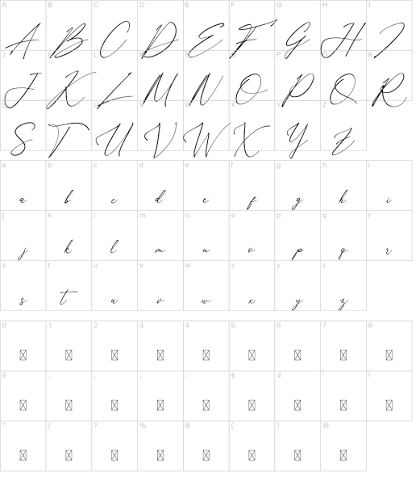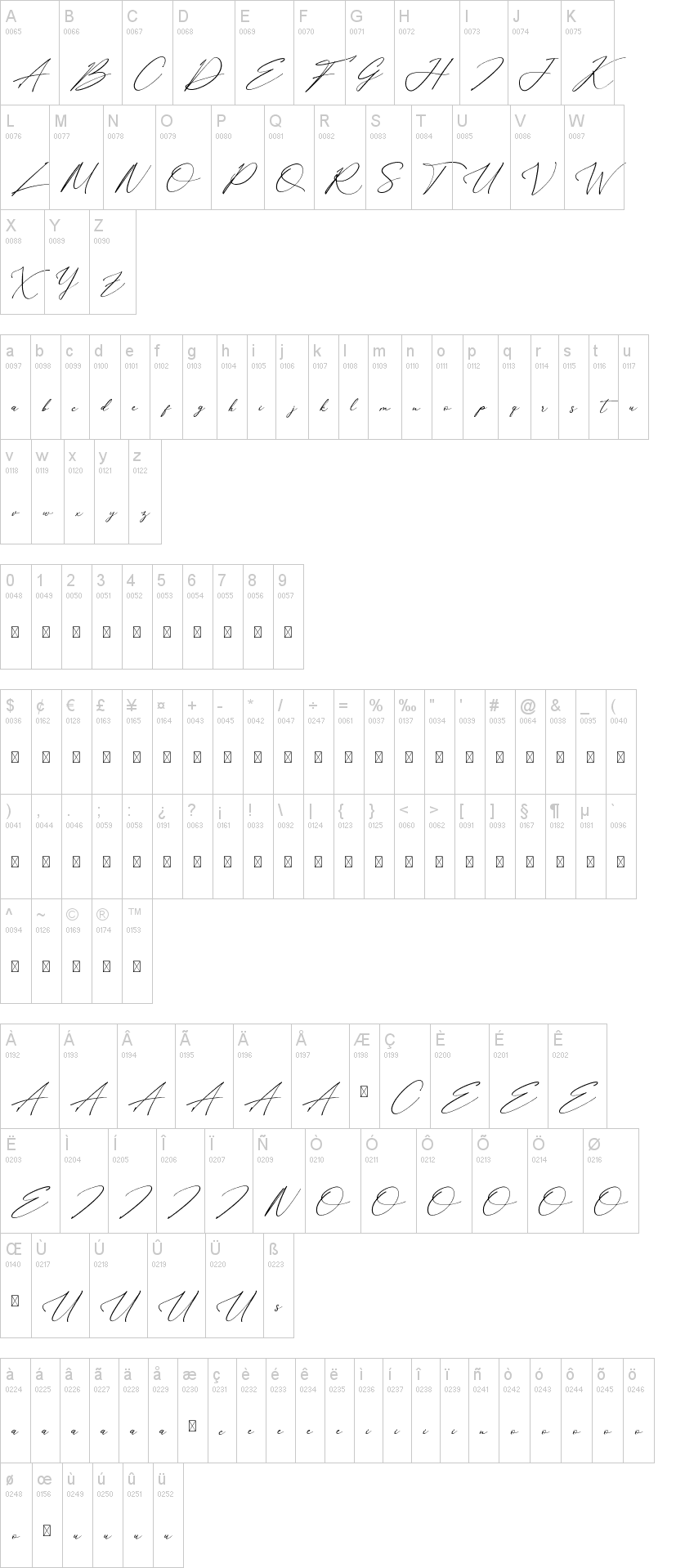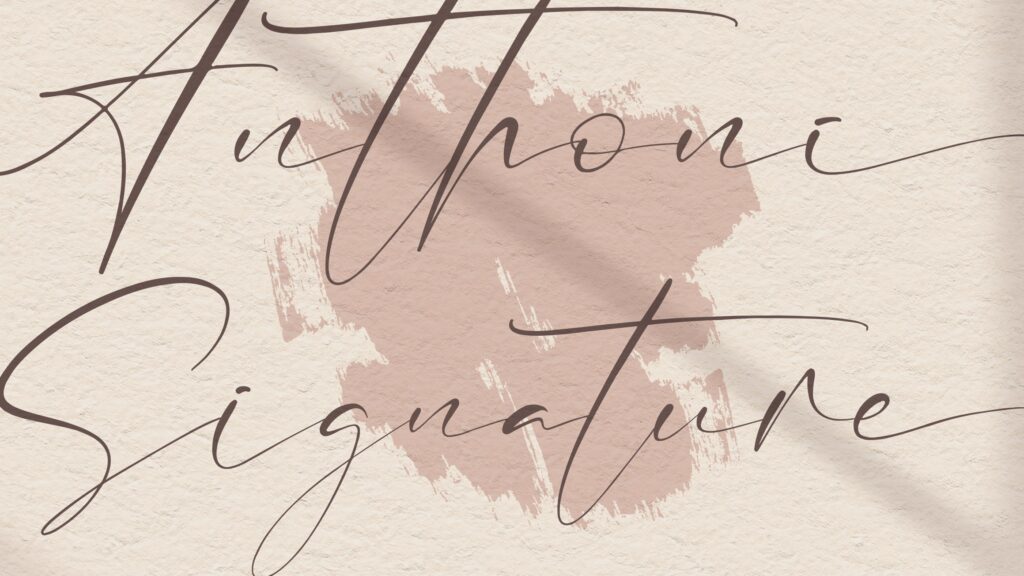
Anthoni Signature font là bộ phông chữ thuộc dòng Signature Script mô phỏng chân thực nét chữ ký tay bằng bút dạ kim cao cấp với các đường nét thanh mảnh, liền mạch và tràn đầy sự tự tin. Mang vẻ ngoài phóng khoáng, hiện đại và đậm dấu ấn cá nhân, kiểu chữ này giúp các kiến trúc sư, nhà thiết kế mang lại sự tinh tế cho các bản vẽ phối cảnh biệt thự sinh thái, sảnh đón tiếp resort sang trọng hay bộ nhận diện thương hiệu kiến trúc đẳng cấp.
Nét bút thanh mảnh và phong thái đĩnh đạc của Anthoni Signature font
Điểm cuốn hút của Anthoni Signature font nằm ở nhịp điệu đưa bút mượt mà, tạo nên các đường liên kết chữ tự nhiên và những nét móc vươn dài đầy thanh thoát. Cấu trúc chữ sở hữu độ mở ký tự thoáng đãng và độ dày nét mảnh dẻ, giúp văn bản toát lên vẻ trang nhã, xóa tan sự cứng nhắc của các khối chữ in ấn truyền thống.
Sự ổn định về mặt cảm xúc của dòng font này giúp truyền tải thông điệp về sự cam kết, tính chuyên nghiệp và sự tận tâm của người kiến tạo không gian. Khi xuất hiện trên các bề mặt vật liệu kiến trúc hiện đại như vách kính trong suốt, kim loại mạ vàng gương hay gỗ tự nhiên sáng màu trong các căn nhà lắp ghép nghỉ dưỡng, Anthoni Signature tạo nên điểm nhấn nhẹ nhàng, làm dịu đi cảm giác thô cứng của các khối kết cấu chịu lực.
| Phân loại phong cách | Signature Script / Monoline / Elegant Handwritten |
| Mục đích phù hợp | Chữ ký kiến trúc sư, biển tên villa, logo cá nhân |
Tư vấn từ chuyên viên: Anthoni Signature sở hữu các đường nét uốn lượn mảnh mai và bay bổng. Để bản thiết kế đạt hiệu quả thẩm mỹ tốt, bạn chỉ nên sử dụng phông chữ này cho các tiêu đề chính, lời tựa ngắn hoặc chữ ký tác giả. Phần nội dung mô tả kỹ thuật chi tiết nên đi kèm một phông chữ không chân thanh mảnh hơn để người xem tiếp nhận thông tin dễ dàng.
03 Ứng dụng phông chữ Anthoni Signature vào công trình thực tế
Nhờ diện mạo lịch thiệp và tính nghệ thuật phong phú, bộ phông chữ này mang lại giá trị thực tế lớn trong khâu tạo điểm nhấn cho các công trình hiện đại:
- Chữ ký Kiến Trúc Sư trên Bản vẽ Ý tưởng: Đặt Anthoni Signature font ở góc bản vẽ phối cảnh 3D như một dấu ấn xác thực của tác giả giúp hồ sơ thiết kế toát lên vẻ chỉn chu và niềm kiêu hãnh của người kiến tạo.
- Biển tên cho Villa và Khu nghỉ dưỡng Cao cấp: Những nét chữ uốn lượn thanh lịch của Anthoni Signature rất ăn ý khi gia công chữ nổi bằng inox vàng xước trên vách đá tự nhiên, mang lại diện mạo sang trọng và chào đón du khách ghé thăm.
- Biển chào mừng và Số phòng cá nhân hóa: Phông chữ này khi khắc laser chìm trên gỗ óc chó hoặc in trên kính mờ sẽ giúp các căn phòng trong khu nhà lắp ghép toát lên chất nghệ thuật tao nhã, mang lại cảm giác được trân trọng cho khách lưu trú.
03 Lưu ý bố cục font Anthoni Signature luôn nhẹ nhàng và bay bổng
Để khai thác hiệu quả vẻ đẹp của dòng font chữ ký này mà không gây cảm giác rối mắt cho bản vẽ, người thiết kế nên lưu tâm một số kinh nghiệm sau:
- Tránh viết hoa toàn bộ cụm từ: Các ký tự hoa của Anthoni Signature có biên độ uốn lượn rộng và nét nối dài. Việc viết hoa liên tiếp nhiều chữ cái sẽ làm các nét xoắn chồng lấn lên nhau, gây mất trật tự bố cục và làm câu văn trở nên khó đọc.
- Kiểm soát khoảng cách dòng: Do các nét vươn lên trên và hạ xuống dưới của phông chữ khá dài, bạn nên thiết lập khoảng cách dòng thoáng đãng để các ký tự không bị chạm nhau, giữ được sự thông thoáng cho khung thiết kế.
- Bố trí nền màu đơn sắc hoặc mờ nhẹ: Anthoni Signature phát huy hiệu quả thị giác cao khi đặt trên các nền màu đơn sắc nhạt hoặc hình ảnh phối cảnh mờ nhẹ, giúp các đường nét thanh mảnh được tôn vinh rõ ràng mà không bị chìm vào chi tiết phụ.